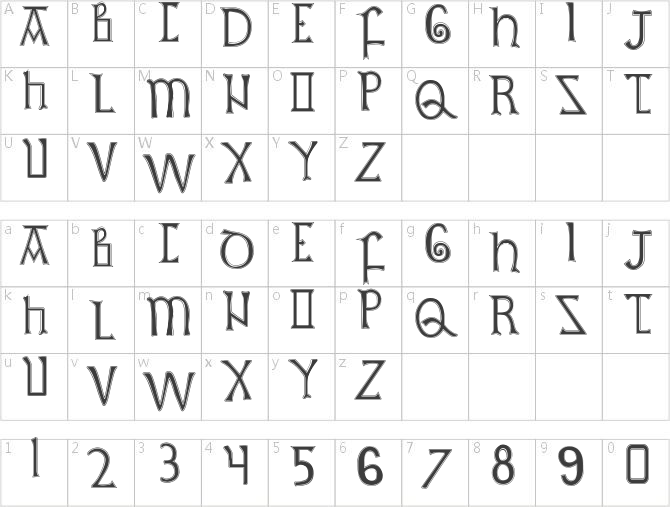
British-Outline-Majuscules 詳情頁(yè)
British-Outline-Majuscules字體字庫(kù)是一款讓人賞心悅目、百看不厭的英文字體,適合各類廣告和產(chǎn)品包裝設(shè)計(jì)應(yīng)用,字體大小0.09MB,格式為ttf字體,上傳用戶是哼哼哈兮,作者/版權(quán)方為未知